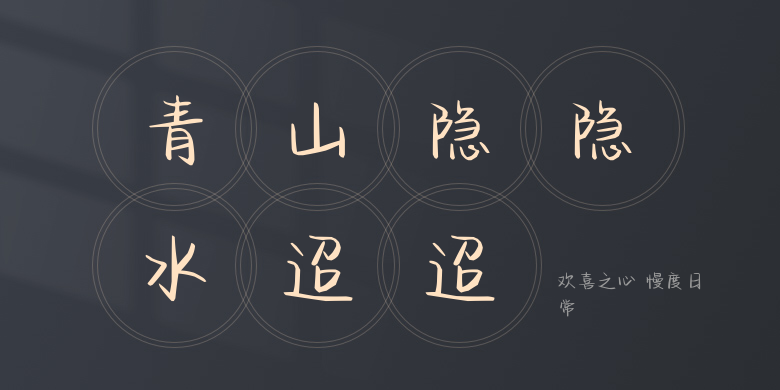
欢喜之心 慢度日常
欢喜之心 慢度日常,这款字体结构工整、笔画清晰,兼顾美观与易读性,适用于标题、正文、海报、包装、LOGO 等多种场景。字形优雅稳定,风格百搭耐看,适配日常排版与创意设计,让文字呈现更舒适、更具质感。欢喜之心 慢度日常一笔一画,皆是细节,以均衡的比例、流畅的线条打造舒适视觉体验,字形端正大气,风格简约现代。无论是商业设计、品牌宣传还是日常排版,都能轻松驾驭,让文字更有格调与力量。欢喜之心 慢度日常字体下载。